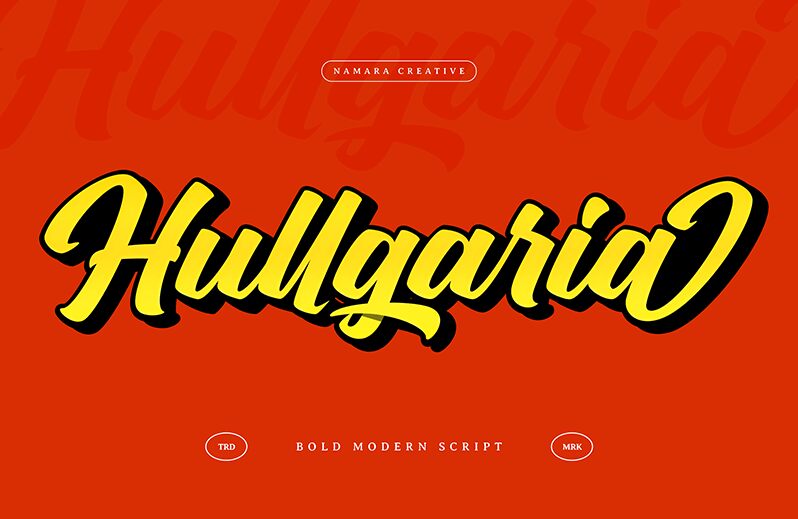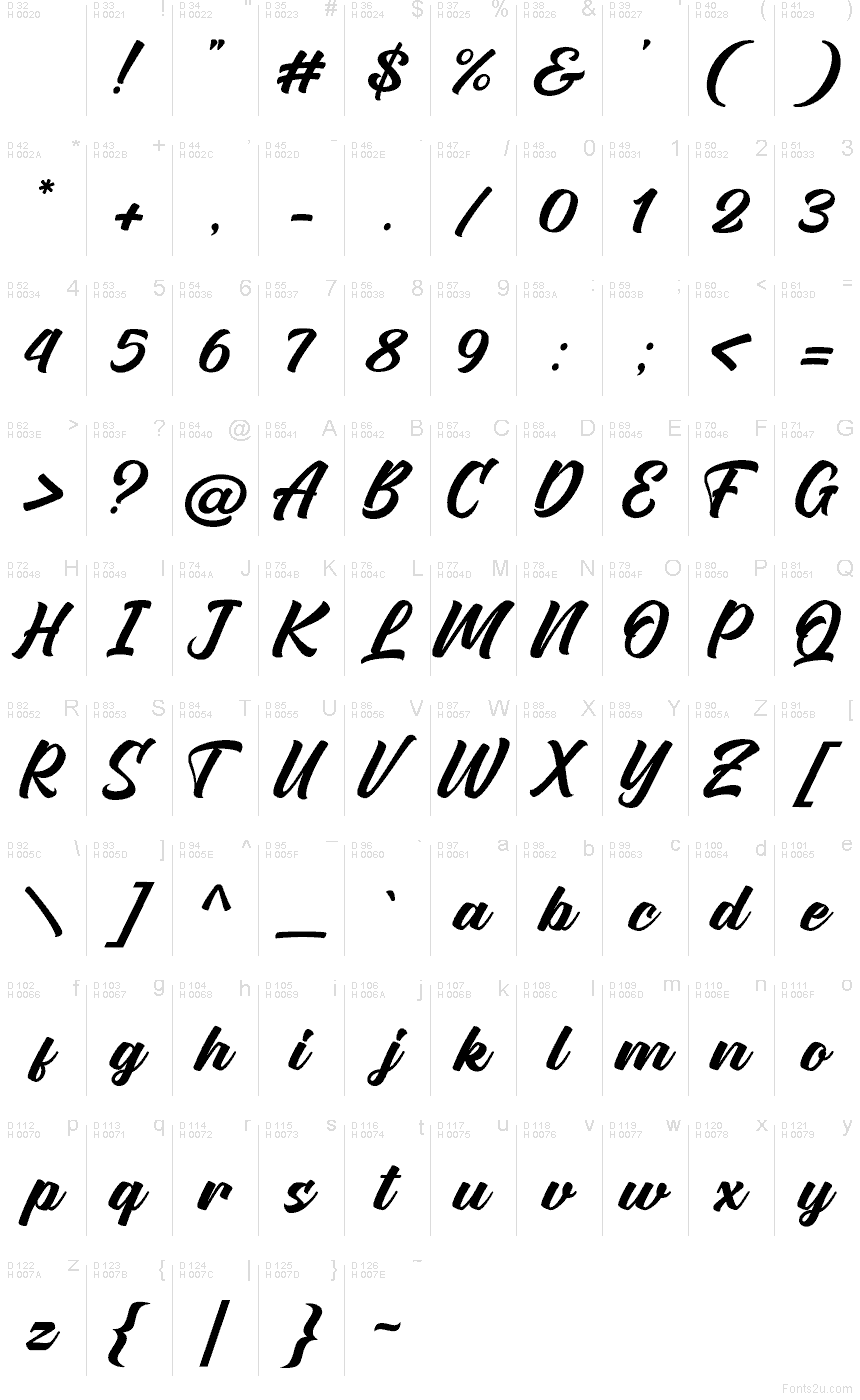
Hullgaria di Namara Creative è un font script tipo pennello gratuito, caratterizzato da un ritmo deciso e un'inclinazione pronunciata. I tratti ampi, le giunzioni fluide e le terminazioni affusolate conferiscono alle lettere un aspetto rapido ed espressivo, mentre la spaziatura ridotta mantiene il movimento compatto ed energico.
Utilizza questo font gratuito per branding di moda, packaging di bevande, poster musicali, copertine di album, grafiche per i social media e titoli. I tratti generosi e le lunghe code finali sono particolarmente efficaci nelle frasi brevi, dove il font ha abbastanza spazio per sostenere la composizione senza perdere il suo carattere spontaneo e scritto a mano.
- Set completo di caratteri standard e punteggiatura.
- Alternative, legature, swash e supporto multilingue.